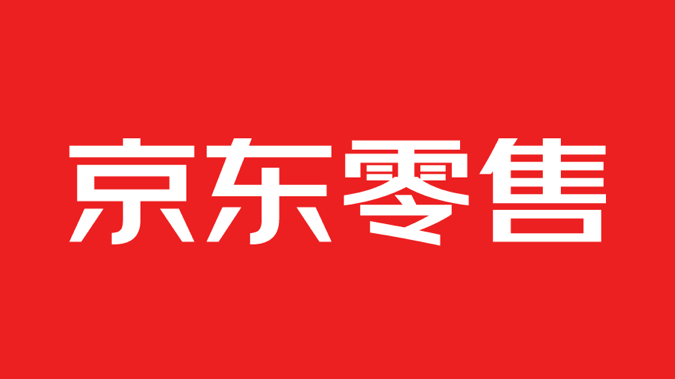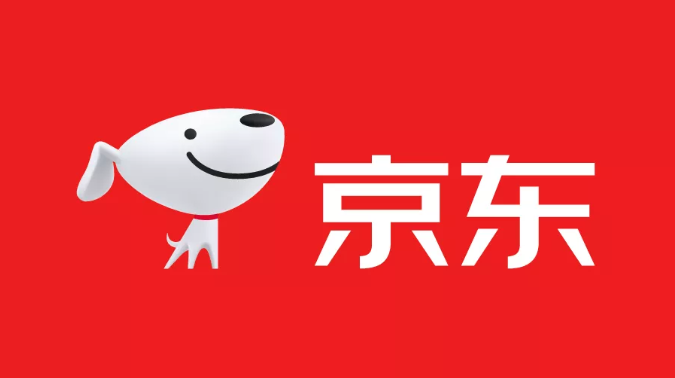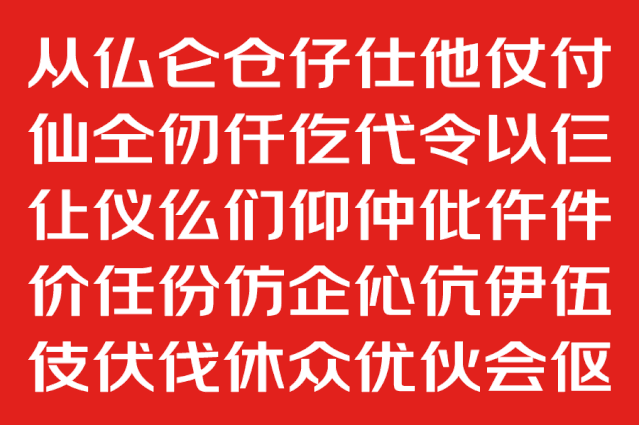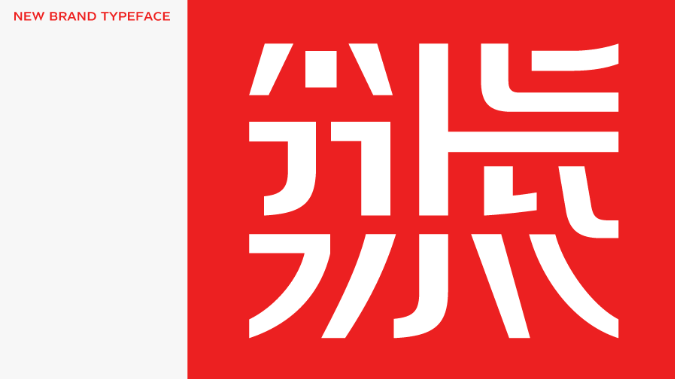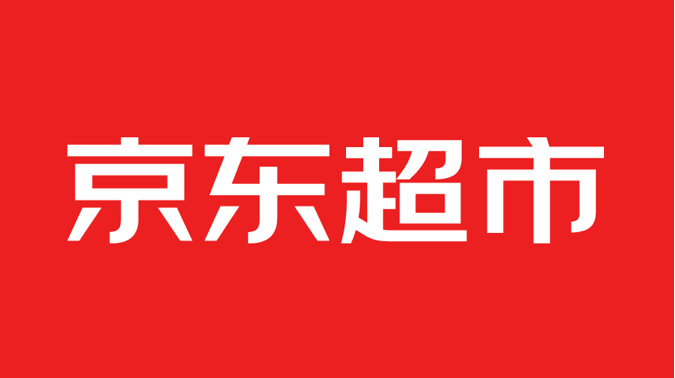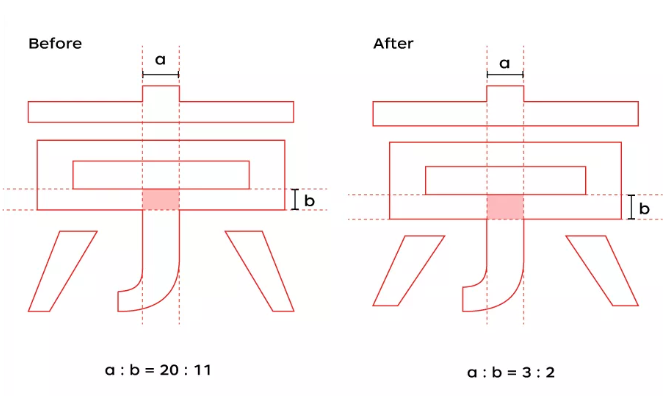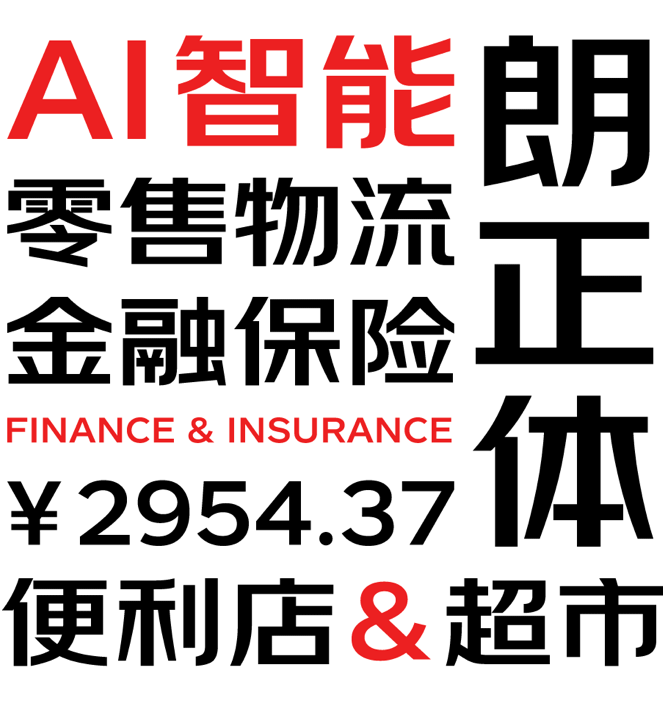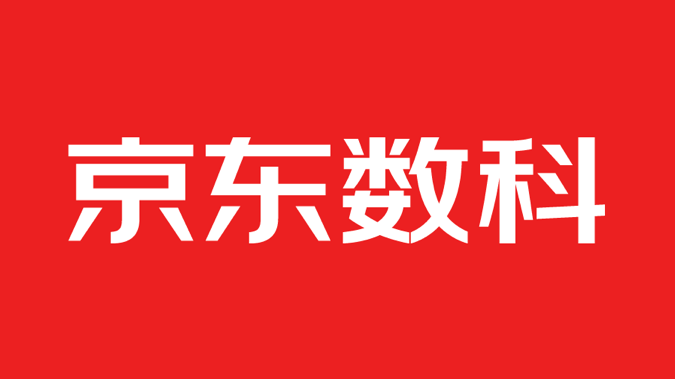
京东朗正体 | 由方正字库设计制作的京东品牌字库
京东发布了全新定制的京东品牌专属字体——京东朗正体,发布后的京东朗正体将广泛应用于京东的品牌文化展示、广告宣传、线下门店等整套视觉系统中,为京东企业文化提供统一且具有高辨识度的标识。
京东朗正体由方正字库团队主导设计,在定制字体方面经验丰富的汪文、仇寅两位老师担任主创设计师。
专用字体,是指企业在塑造品牌形象的过程中,为确立一个既强烈且统一的形象,而固定选用的符合品牌定位的一款或多款字体。大到企业的品牌标识、产品广告,小至企业印刷宣传品、日常推广物料,都能够以专用字体的特色和规范为核心基础而展开设计。
在大众的印象中,京东是一个成熟而专业的大型综合型电商平台,一向以品质精良、高效送达、用户体验友好著称。如今,京东正在朝向更加开放、更加多元的方向高速驰骋着,以成为全球最值得信赖的企业为目标。在这个背景下,具有高识别度并融汇着京东企业文化特色的专属字体——京东朗正体诞生了,它承载着让世界更好地认识京东的使命。
基于京东品牌的定位,以及一直奉行的客户为先、诚信、协作、感恩、拼搏、担当的价值观,京东朗正体的品牌识别度关键词落脚在了力量感、科技感、直接、简洁、友好五个维度上,并以此为设计理念来发散设计。
以“京东”二字为例,首先,我们对横竖比例进行了调整。原来的“京东”二字,横比较细竖比较粗,为了强化力量感的传达,设计师反复思考、不断尝试,最后将字体横竖比例定为了2:3。横竖比例的改变,让整个字的灰度变得稳定、均匀,也显得更稳重、更有力量感。
其次,为了让字体更具时尚感、更适合阅读,设计师对字体结构进行了调整,将中宫稍微缩小了一点。中宫缩小之后,更有呼吸感,阅读起来会更顺畅,体验会更加友好。同时,中宫的缩小,让撇和捺显得更舒展,整个字体气质也变得稍微内敛、更具人文性一些。